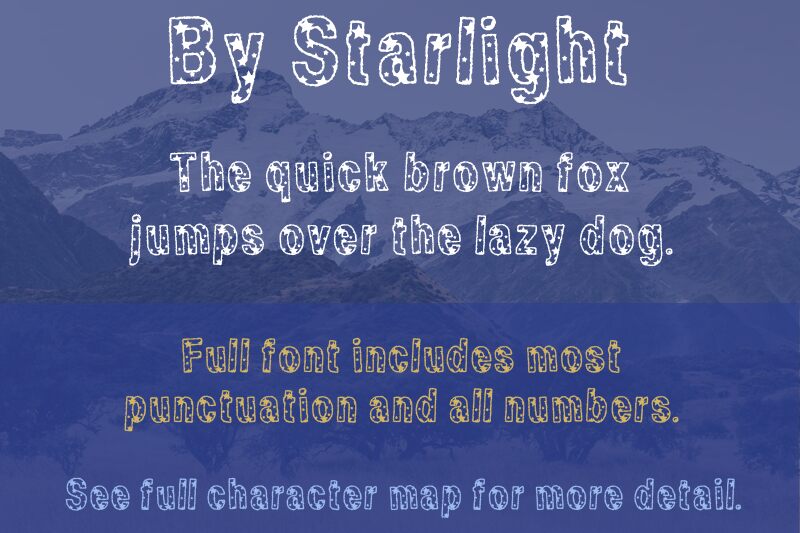
By Starlight von Lauren C. Brown ist eine kostenlose, dekorative Display-Schrift, die aussieht, als wäre sie aus tintengetränktem Papier ausgeschnitten und mit Sternen aus der Nacht übersät. Klobige Buchstaben, geprägt von fetten Sternformen und rauen, skizzenhaften Kanten, verleihen ihr einen verspielten, leicht grungy Charakter – wie Kritzeleien am Rand eines Lieblingsnotizbuchs. Sie sorgt sofort für einen Hauch von Magie, Schelmerei und handgemachtem Charme, wo immer sie auftaucht.
Mit By Starlight lassen sich Einladungen zu Kinderpartys, Flyer für Übernachtungspartys, Buchtitel, Sticker, Poster und fantasievolle Social-Media-Grafiken wunderbar in Szene setzen. Diese kostenlose Schrift glänzt besonders in großen Größen, damit die sternenreiche Textur richtig zur Geltung kommt; kombinieren Sie den Begleittext für ein ausgewogenes Bild mit einer schlichten serifenlosen Schrift. By Starlight verwandelt jede Überschrift in eine kleine Galaxie, die Aufmerksamkeit erregt und dabei Spaß macht, warm und ein wenig wild wirkt.
Die By Starlight Schrift wurde im Dezember 2000 fertiggestellt; zwei frühere Versionen wurden erstellt und anschließend verworfen.
Sie enthält Groß- und Kleinbuchstaben, Zahlen und Satzzeichen.